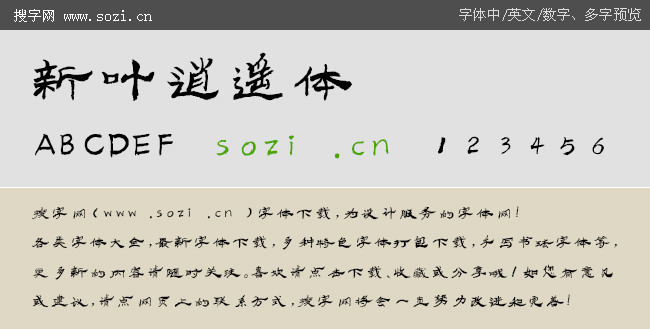
新葉逍遙體
搜字網(wǎng)給大家提供一款新葉逍遙體中文手寫書法字體下載,新葉逍遙體由新葉傳媒制作,當你看到新葉逍遙體的時候,看著它一筆一畫的橫成飄逸,縹緲隨性,你心里突然蹦出扶搖而上九萬里的字句,你的心都開始跟著飄搖起來了。這就是逍遙體的魅力,讓你發(fā)現(xiàn)原來大廈高樓里,也存在你喜歡的逍遙人生。適用于包裝設計、海報設計等應用!敬丝钭煮w可供個人非商業(yè)免費使用,商用請關(guān)注公眾號“新葉傳媒”進行購買使用】 此次新葉逍遙體全新推出,給力活動拉開序幕!限時活動,不定期漲價! 1.個人包年29.9,個人永久69.9 2.企業(yè)包年89.9,企業(yè)永久199 還在等什么?這么漂亮帥氣的你,趕快支持原創(chuàng)吧!